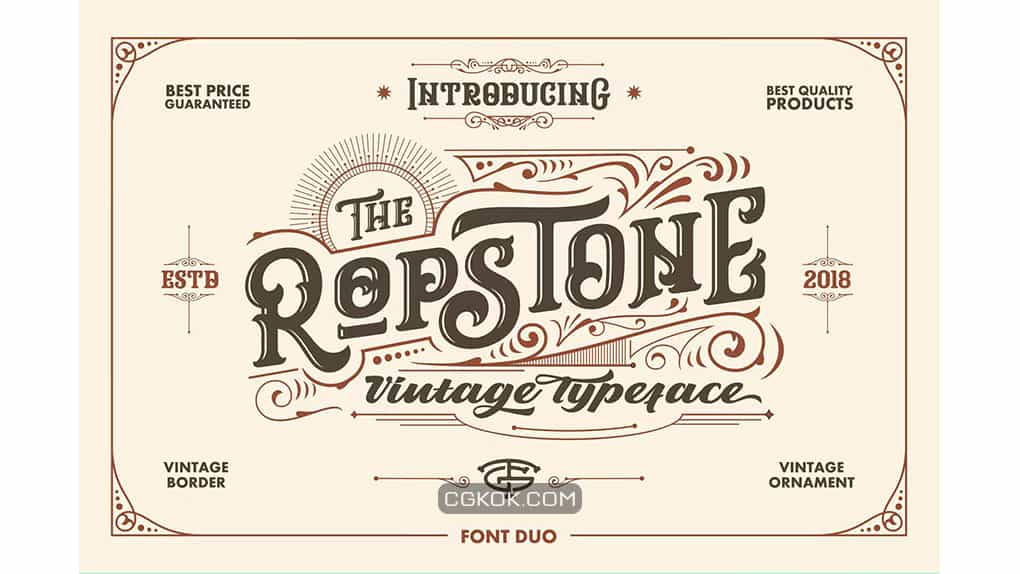
فونت انگلیسی کلاسیک Ropstone Typeface : این مجموعه یک فونت دستنویس است که با الهام از پوستر های کلاسیک طراحی شده است. با این فونت میتوانید به متون خود استایل وینتیج ببخشید.
- سبک: Serif
- فضا بین حروف: معمولی
- اندازه بهینه: بزرگ (نمایش / پوستر)